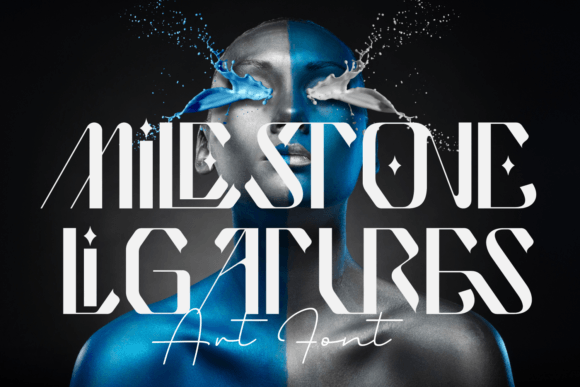
Milestone Ligatures
Conçu avec précision, Milestone Ligatures offre des vecteurs nets, une typographie fluide et une licence commerciale pour une tranquillité d'esprit.